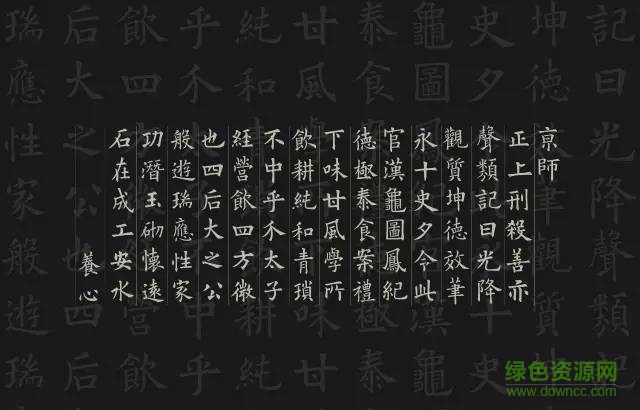
汉仪欧楷字体是一款汉仪类正规楷体风格字体软件,欧楷体一笔一画一丝不苟,粗细相间,优雅气息十足,非常的醒目养眼,还有更多类似好看字体欢迎来绿色资源网下载体验!
汉仪欧楷字体是一款应用于艺术设计方面的简体中文字体,该字体笔画粗壮,尾部的甩尾有力且有丰富的笔触细节,大字效果突出且引人注目;并且最大程度还原作者书写字形,细节表现完整,且字库完整,可以广泛应用于名片设计、新闻媒体、宣传海报、ppt、影视制作以及内容用字等领域。
该字体粗细相间,给个字所占空间大小一致,尽显楷体的正规,整体效果十分优美好看,用来装帅再合适不过了!